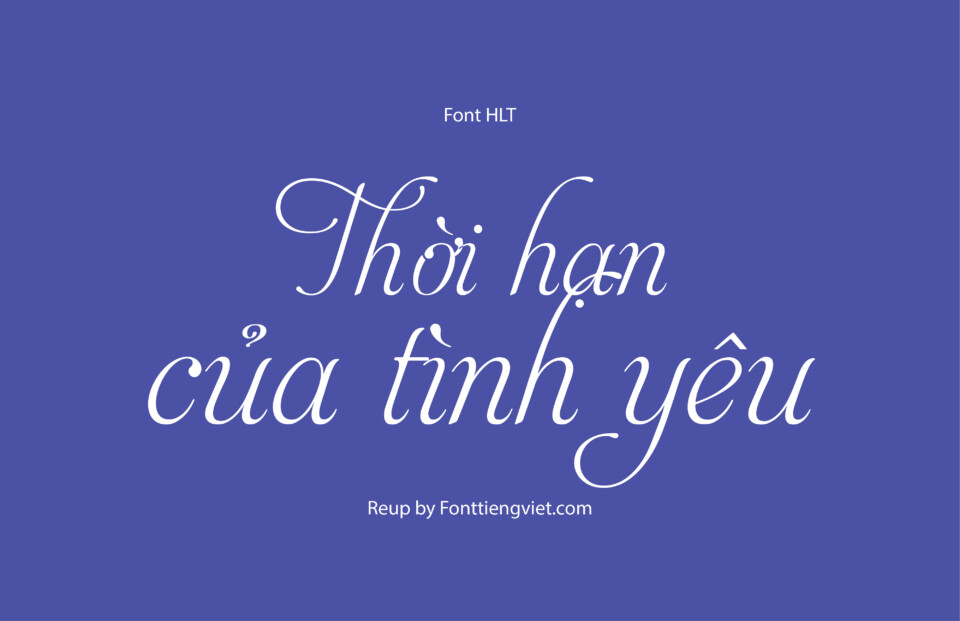
Font Việt hóa HLT AphroditeSlimPro
Giới thiệu về Font Việt hóa HLT AphroditeSlimPro
Trong thế giới thiết kế đồ họa hiện đại, việc tìm kiếm một bộ Font Miễn Phí chất lượng cao là nhu cầu thiết yếu của nhiều người dùng tại Việt Nam. Font Việt hóa HLT AphroditeSlimPro nổi lên như một sự lựa chọn hoàn hảo dành cho những ai yêu thích phong cách thư pháp thanh lịch và sang trọng. Đây là bộ font mang đậm nét nghệ thuật cổ điển nhưng vẫn giữ được sự tinh tế cần thiết để phù hợp với các xu hướng trình bày văn bản ngày nay.
Nguồn gốc và đặc điểm nổi bật
Bộ font này nguyên gốc được thiết kế bởi các chuyên gia quốc tế với hàng nghìn ký tự thay thế đặc biệt. Khi được đội ngũ HLT thực hiện quy chuẩn tiếng Việt, Font Việt hóa HLT AphroditeSlimPro đã giữ trọn vẹn các đường nét uốn lượn mềm mại và các ký tự móc nối tự nhiên. Nhờ đó, người dùng có thể dễ dàng tạo ra những bản thiết kế thiệp mời, bìa sách hay các ấn phẩm giáo dục đầy ấn tượng mà không lo bị lỗi hiển thị dấu câu.
Ứng dụng thực tế của bộ font trong thiết kế
Với hơn 1000 ký tự đồ họa đi kèm, bộ font này cho phép học sinh và giáo viên sáng tạo không giới hạn. Bạn có thể sử dụng Font Việt hóa HLT AphroditeSlimPro để trang trí tiêu đề bài giảng, làm báo tường hoặc thiết kế các chứng nhận khen thưởng cho nhà trường. Sự đa dạng trong các biến thể ký tự giúp mỗi dòng chữ trở nên độc bản và mang tính cá nhân hóa cao.